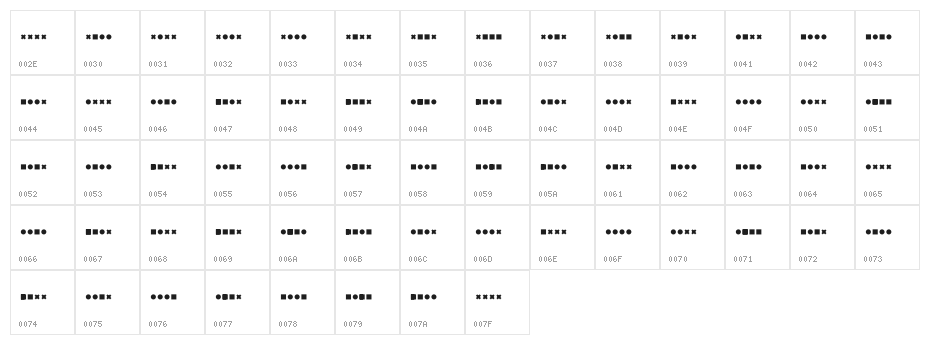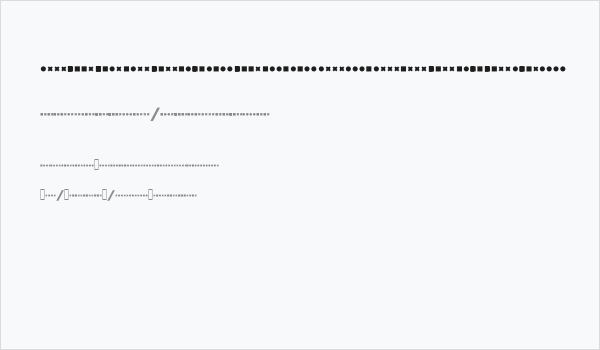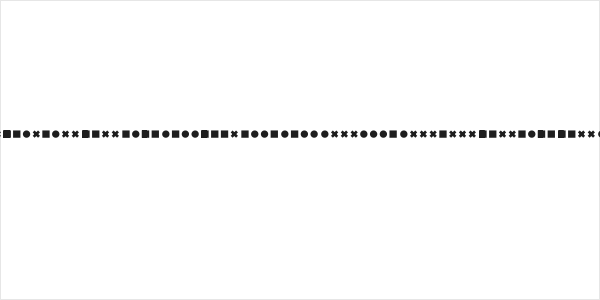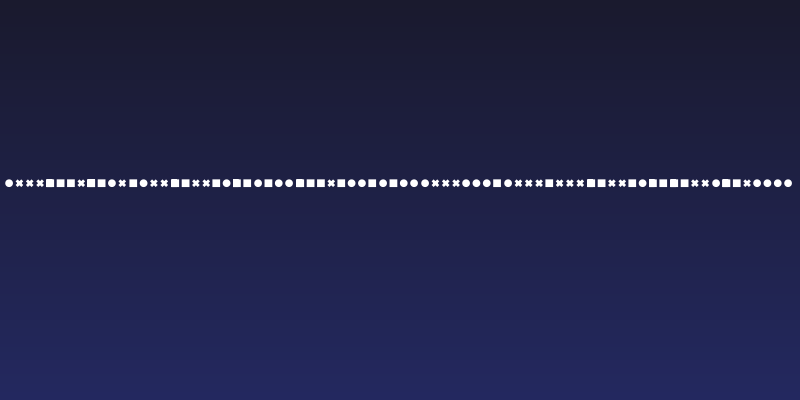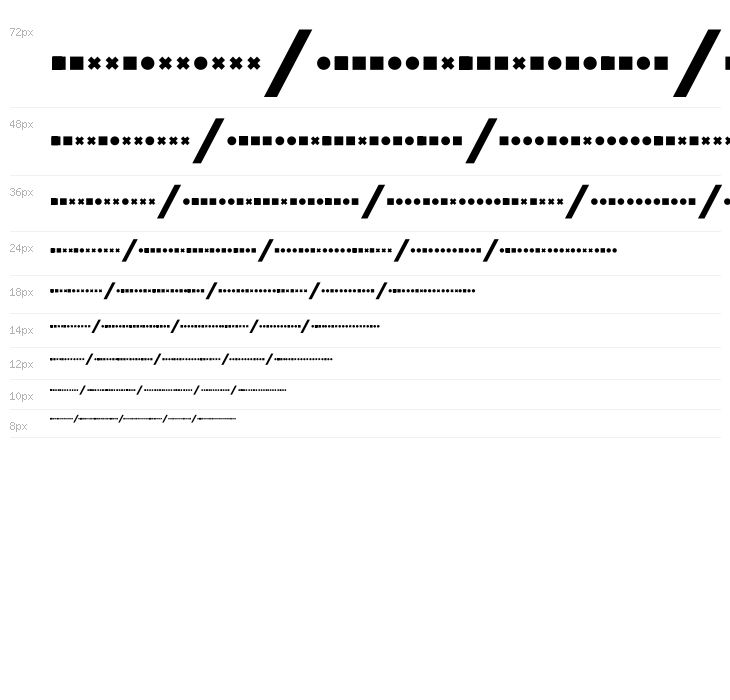
EightySixSeventyTwo Font
| Stil general | Abstract |
| Caz de utilizare | Decorative elements, Abstract art |
| Proiecte propuse | This design could be used for abstract art projects or as a decorative element in graphic design, but not for text-based applications. |